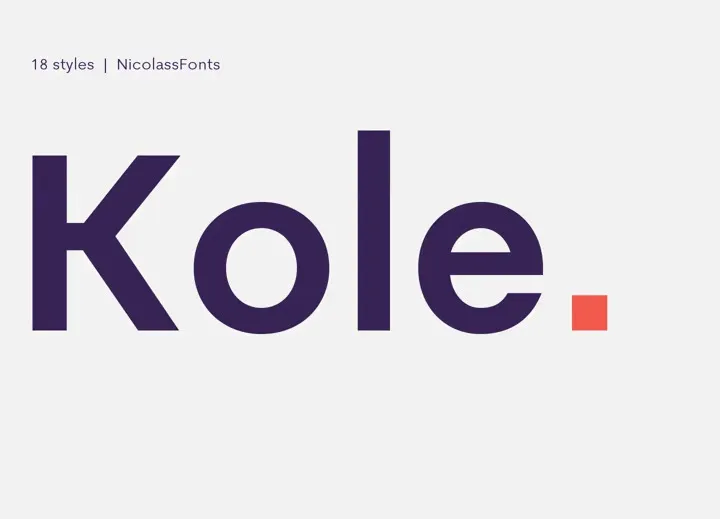
Kole Font – Download Grátis
A Kole Font é uma nova família de tipo geométrico e sans-serif que traz um estilo elegante e moderno. Feita pelo designer NicolassFonts, esta família completa contém 18 pesos diferentes. Perfeita para uso em rótulos, embalagens, identidade de marca, software, design editorial, web e design para tela, a Kole é especialmente adequada para headlines e logotipos. Idealmente projetada para expressar uma variedade de mensagens de maneira clara e impactante, sem perder a elegância característica deste tipo de fonte. Engajantes tanto em aplicações offline quanto online, a Kole oferece um conjunto completo que é perfeito para o seu próximo projeto visual.